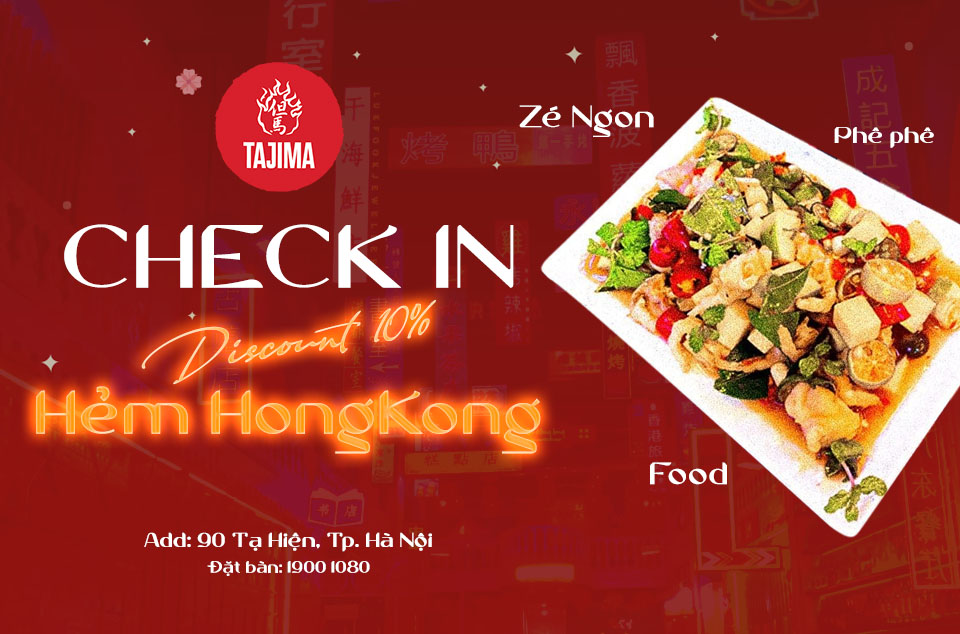
Font việt hóa 1FTV thiết kế ẩm thực 2
Tìm hiểu về bộ Font việt hóa 1FTV thiết kế ẩm thực 2
Trong lĩnh vực thiết kế đồ họa dành cho ngành dịch vụ ăn uống, việc lựa chọn phông chữ đóng vai trò then chốt để tạo nên linh hồn cho thương hiệu. Font việt hóa 1FTV thiết kế ẩm thực 2 là một giải pháp hoàn hảo cho những ai đang tìm kiếm sự kết hợp giữa nét hiện đại và phong vị truyền thống. Khi sử dụng Font Miễn Phí để sáng tạo, người thiết kế có thể dễ dàng truyền tải cảm giác ngon miệng và sự gần gũi đến với khách hàng thông qua từng con chữ được trau chuốt kỹ lưỡng.
Tại sao nên chọn Font việt hóa 1FTV thiết kế ẩm thực 2?
Bộ phông chữ này được tối ưu hóa đặc biệt cho các bảng mã tiếng Việt, giúp khắc phục hoàn toàn lỗi hiển thị dấu – một vấn đề thường gặp ở các phông chữ ngoại nhập. Với Font việt hóa 1FTV thiết kế ẩm thực 2, bạn sẽ sở hữu những đường nét uốn lượn mềm mại nhưng vẫn giữ được độ dày cần thiết để tạo điểm nhấn trên menu hoặc biển quảng cáo. Sự linh hoạt của bộ font này cho phép áp dụng rộng rãi từ các quán ăn đường phố bình dân đến những nhà hàng sang trọng, mang lại hiệu ứng thị giác mạnh mẽ ngay từ cái nhìn đầu tiên.
Ứng dụng Font việt hóa 1FTV thiết kế ẩm thực 2 vào dự án thực tế
Khả năng ứng dụng của bộ font này cực kỳ đa dạng nhờ vào cấu trúc chữ cân đối và dễ đọc. Dưới đây là những cách mà bạn có thể khai thác tối đa sức mạnh của nó trong thiết kế.
Thiết kế thực đơn và Poster quảng cáo
Đối với một tờ thực đơn, tiêu đề món ăn cần phải nổi bật và hấp dẫn. Font việt hóa 1FTV thiết kế ẩm thực 2 cung cấp các ký tự có độ tương phản cao, giúp người xem dễ dàng ghi nhớ tên món. Ngoài ra, khi kết hợp với các hình ảnh món ăn rực rỡ trên poster, bộ font này giúp tạo nên một tổng thể hài hòa, kích thích vị giác của thực khách một cách tự nhiên nhất. Các designer thường ưa chuộng dùng nó cho các cụm từ nhấn mạnh như “Khuyến mãi đặc biệt” hoặc “Món ngon mỗi ngày”.
Xây dựng bộ nhận diện thương hiệu ngành F&B
Logo của một quán cà phê hay tiệm bánh đòi hỏi sự độc bản và dễ nhận diện. Việc sử dụng Font việt hóa 1FTV thiết kế ẩm thực 2 trong thiết kế logo giúp thương hiệu trông chuyên nghiệp và có gu thẩm mỹ riêng. Không chỉ dừng lại ở bảng hiệu, bạn còn có thể dùng font này để in ấn trên bao bì, khăn giấy hay đồng phục nhân viên, tạo ra sự đồng bộ tuyệt đối trong trải nghiệm khách hàng. Đây chính là công cụ đắc lực để kể câu chuyện ẩm thực thông qua ngôn ngữ thiết kế thị giác tinh tế.
Kết luận về bộ Font việt hóa 1FTV thiết kế ẩm thực 2